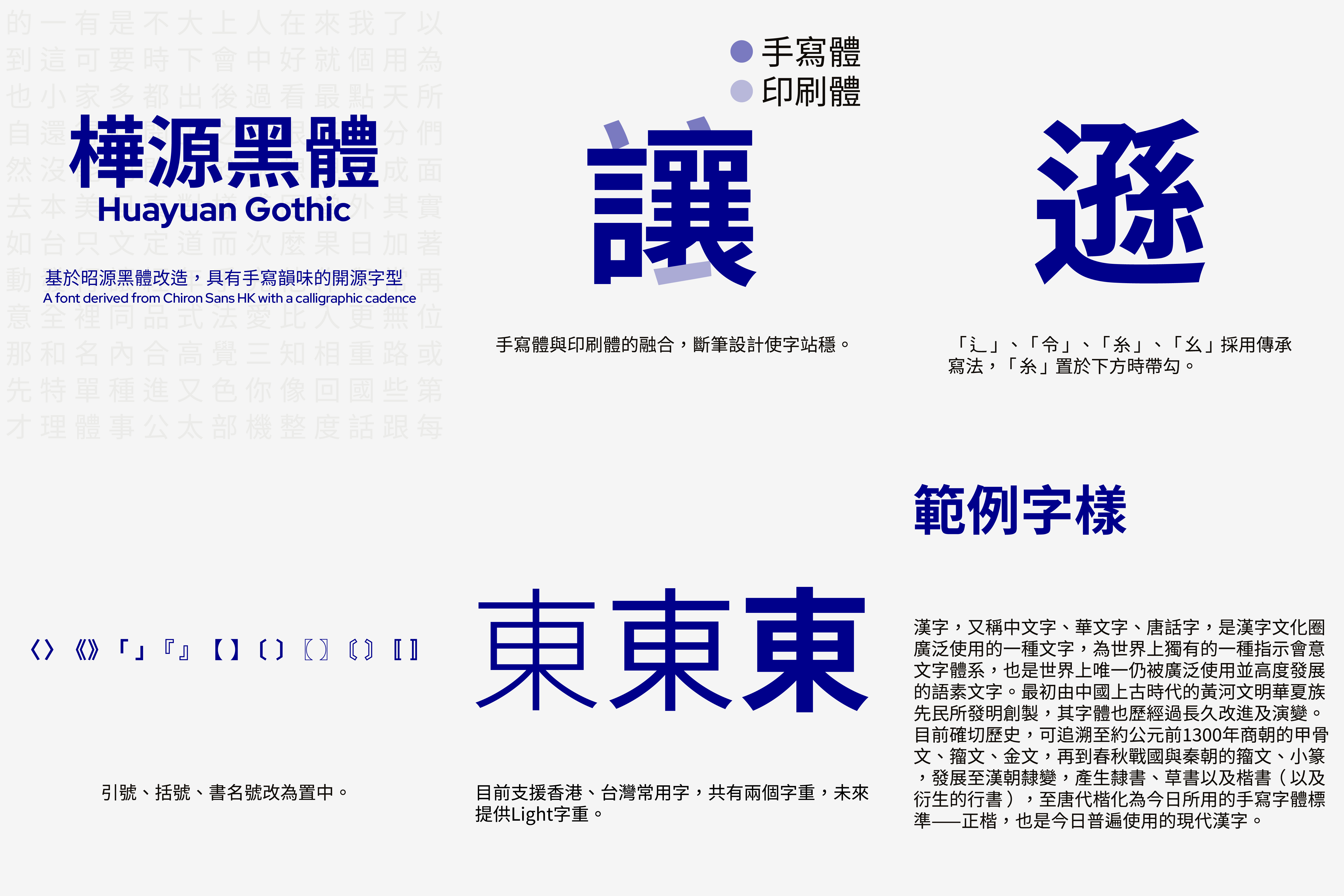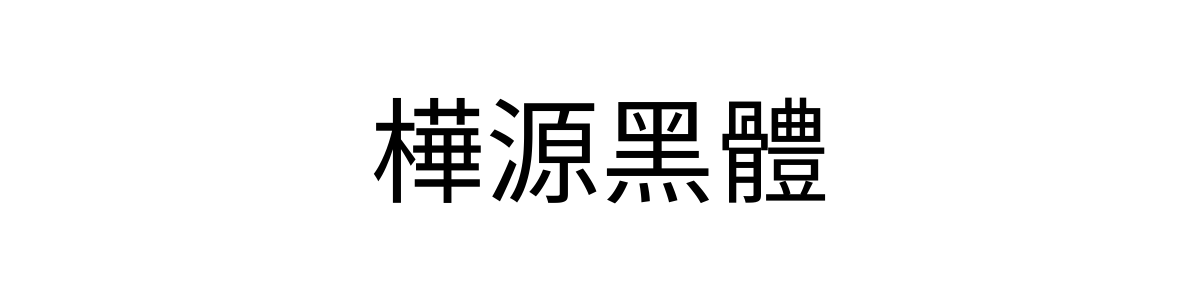
桦源黑体
桦源黑体(Huayuan Gothic)是一款基于昭源黑体思源黑体改造,并融入传统手写韵味的开源繁体中文黑体。该字体在昭源黑体(其本身源自思源黑体香港版)清晰、现代的骨架基础上,进行了关键性的风格化处理,为核心的黑体结构注入了来自手写楷书的笔意与韵味。
部分字形参考或取自台北黑体,进一步丰富了其字形来源与细节表现。目前字体主要支持香港、台湾地区的常用繁体中文,包含两个字重。
字体风格
桦源黑体保留了昭源/思源黑体家族均衡、清晰的中性结构,设计师有意识地将手写楷书或旧铅字中的某些笔形特征与韵味,渗透到标准黑体的笔画之中。
这种融合可能体现在:笔画末端微妙自然的弧度与粗细变化(而非绝对的平直切割)、转折处略带圆润的处理、以及某些部首结构参照了更具书法感的传统写法。